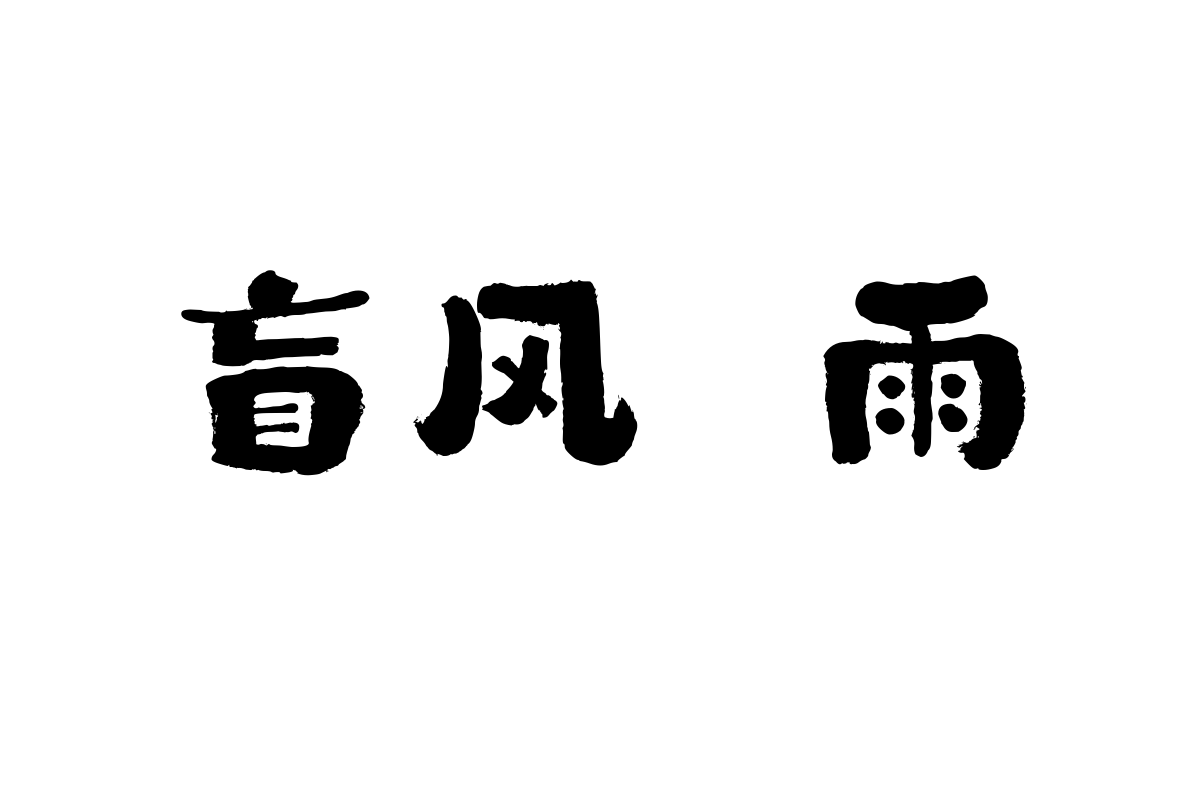
山海白茶手书w是一款手写体,具有独特的风格和韵味。这款字体由设计师精心打造,旨在为使用者提供一种独特而富有个性的书写体验。
特点:
1. 笔触流畅:山海白茶手书w的笔触非常流畅,给人一种轻松愉悦的感觉。
2. 字形优美:这款字体的字形设计独特,线条柔和,给人一种优雅而高贵的感觉。
3. 易于识别:虽然这款字体看起来复杂,但实际上非常容易识别和模仿。
4. 适用于多种场景:无论是用于手写笔记、签名还是设计作品,山海白茶手书w都能展现出其独特的魅力。
总之,山海白茶手书w是一款非常值得尝试的手写体,它不仅具有独特的风格和韵味,而且易于识别和应用。